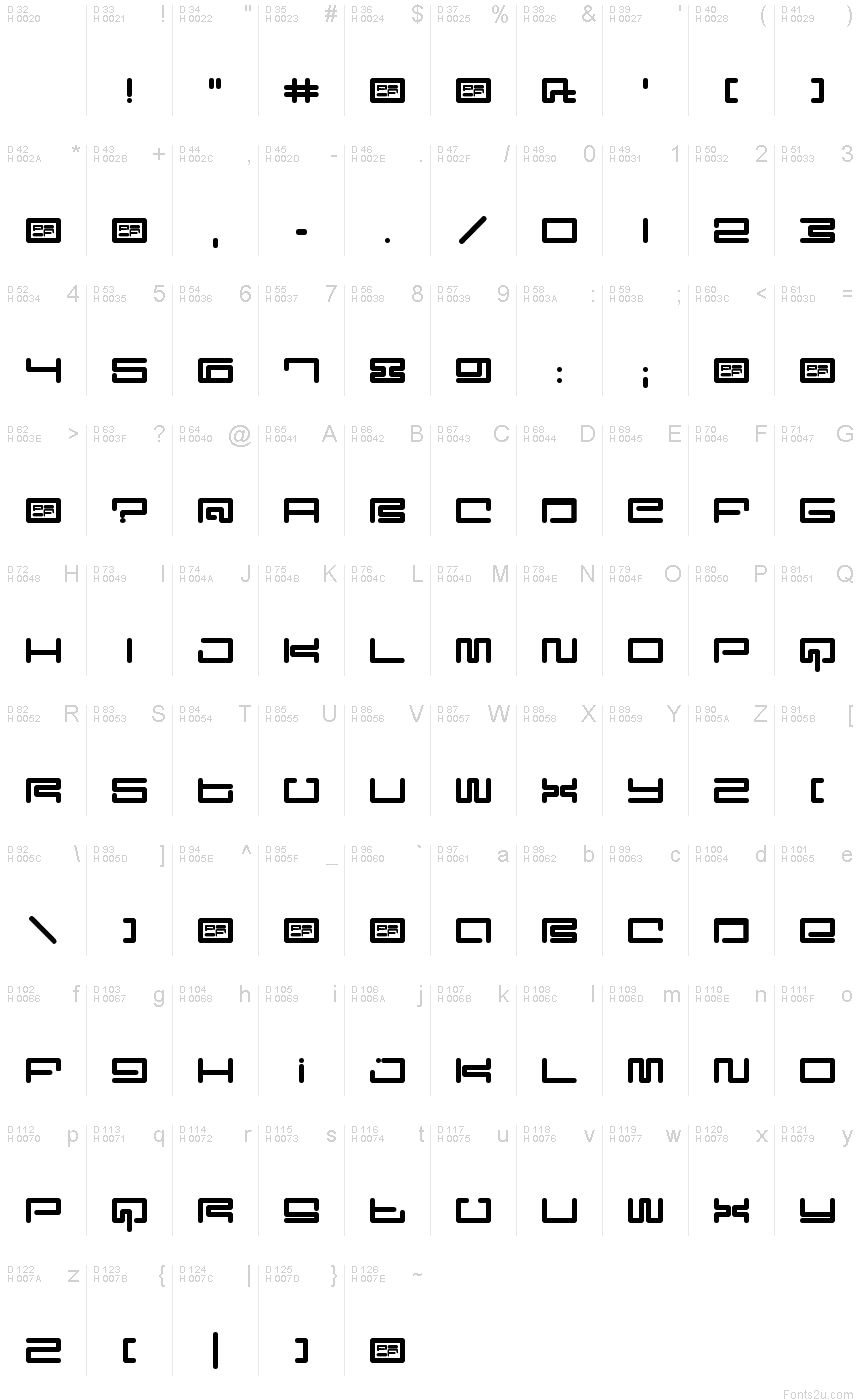
Digit Cube, entworfen von Digit Cube für Font"a"licious Fonts, ist eine kostenlose, futuristische Display-Schrift aus breiten, geometrischen Strichen. Abgerundete Ecken und eckige Öffnungen verleihen dem Schriftbild das Aussehen einer kompakten digitalen Benutzeroberfläche.
Technologie-Branding und Club-Grafiken greifen auf unterschiedliche Weise auf ihren elektronischen Stil zurück. Sie kann auch Spielmenüs und Albumcover prägen, besonders wenn ein eleganter Look der späten 1990er-Jahre zum Thema passt. Im Editorial Design können die breiten modularen Formen einen Magazin-Ressorttitel in ein oberflächenähnliches grafisches Element verwandeln.